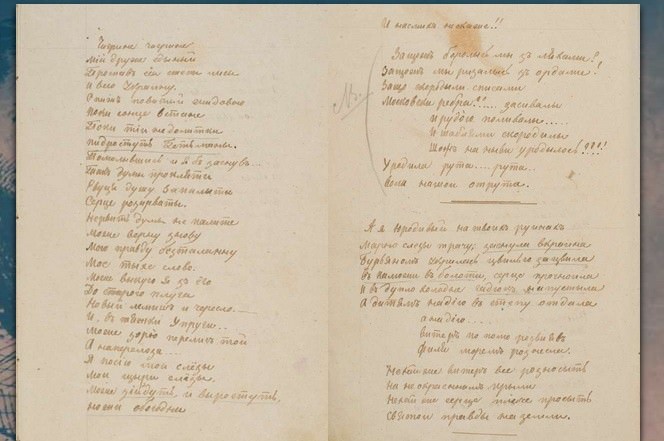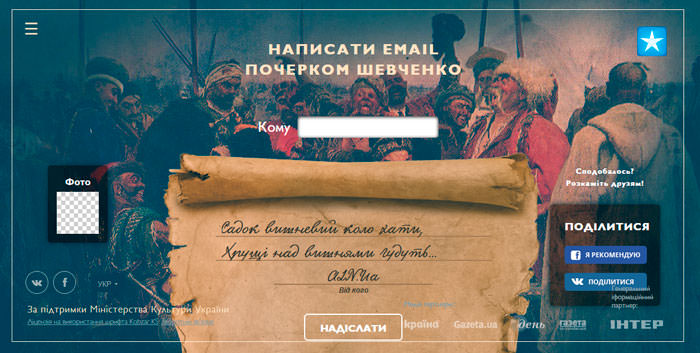
Тепер кожен зможе писати як Тарас Григорович Шевченко. До двухсотої річниці дня народження Кобзаря, був розроблений шрифт Kobzar KS, який повністю відтворює його почерк. В ньому присутні латинські та кирилічні букви, підтримуються біля 100 мов.
Шрифт був створений українськими графічними дизайнерами: Дмитром Растворцем, Лук’яном Турецьким і Геннадієм Заречнюком, базуючись на факсимільному виданні рукописної збірки «Три літа», котра зберігається в інституті літератури ім. Т.Г.Шевченка. Дизайнери оцифрували збірку і створили шрифт з усіма необхідними елементами сучасного цифрового дизайну.